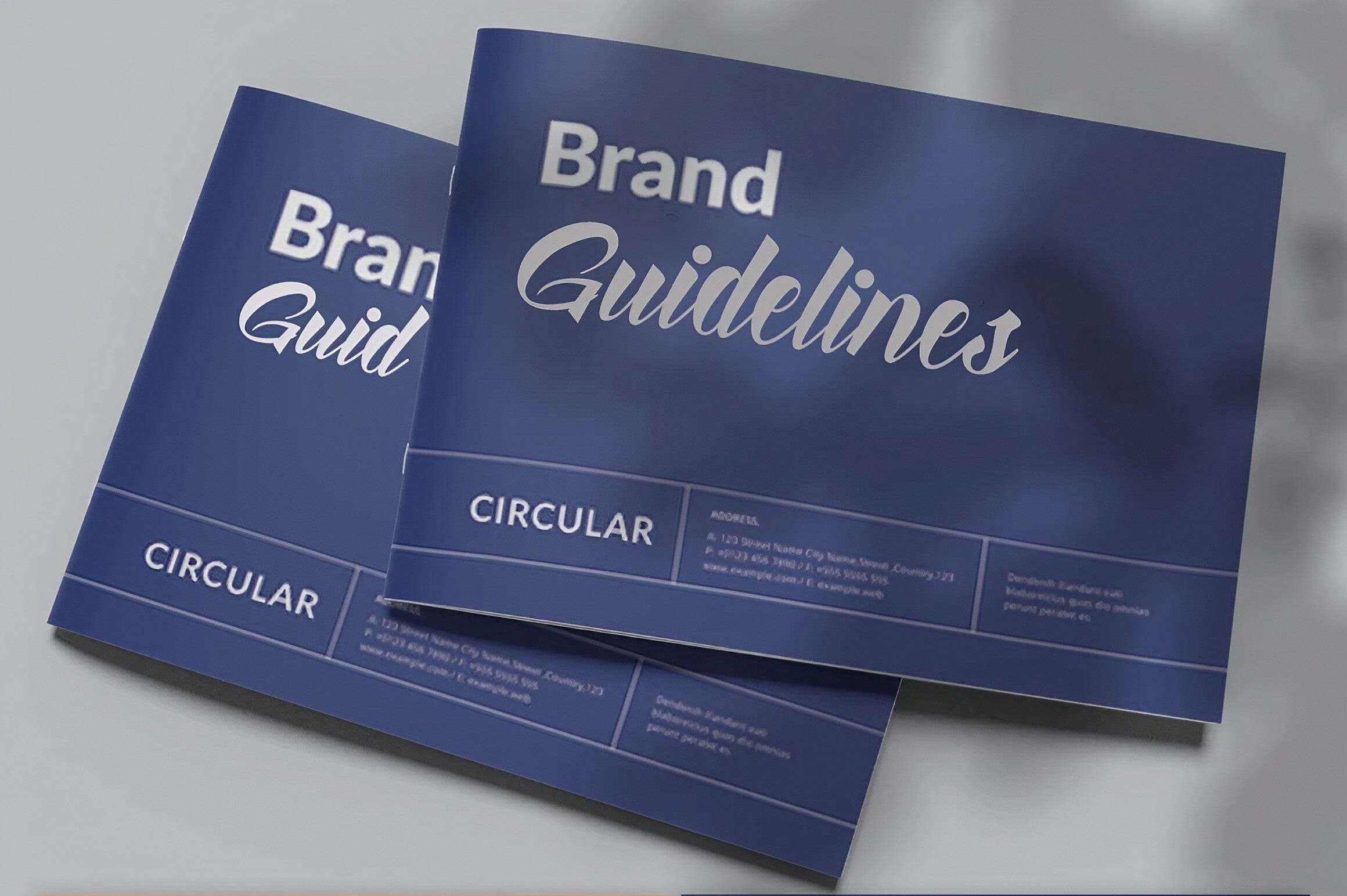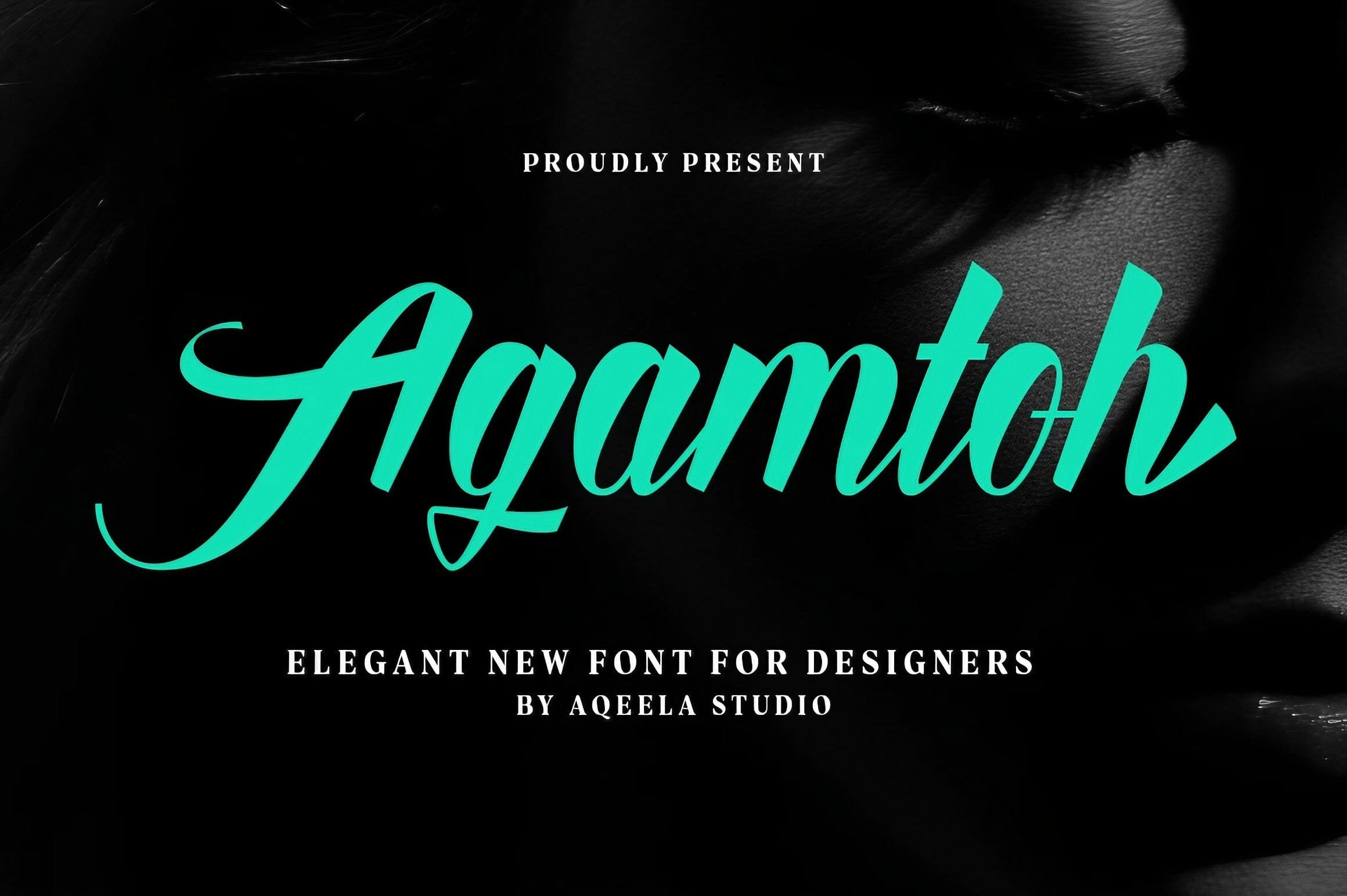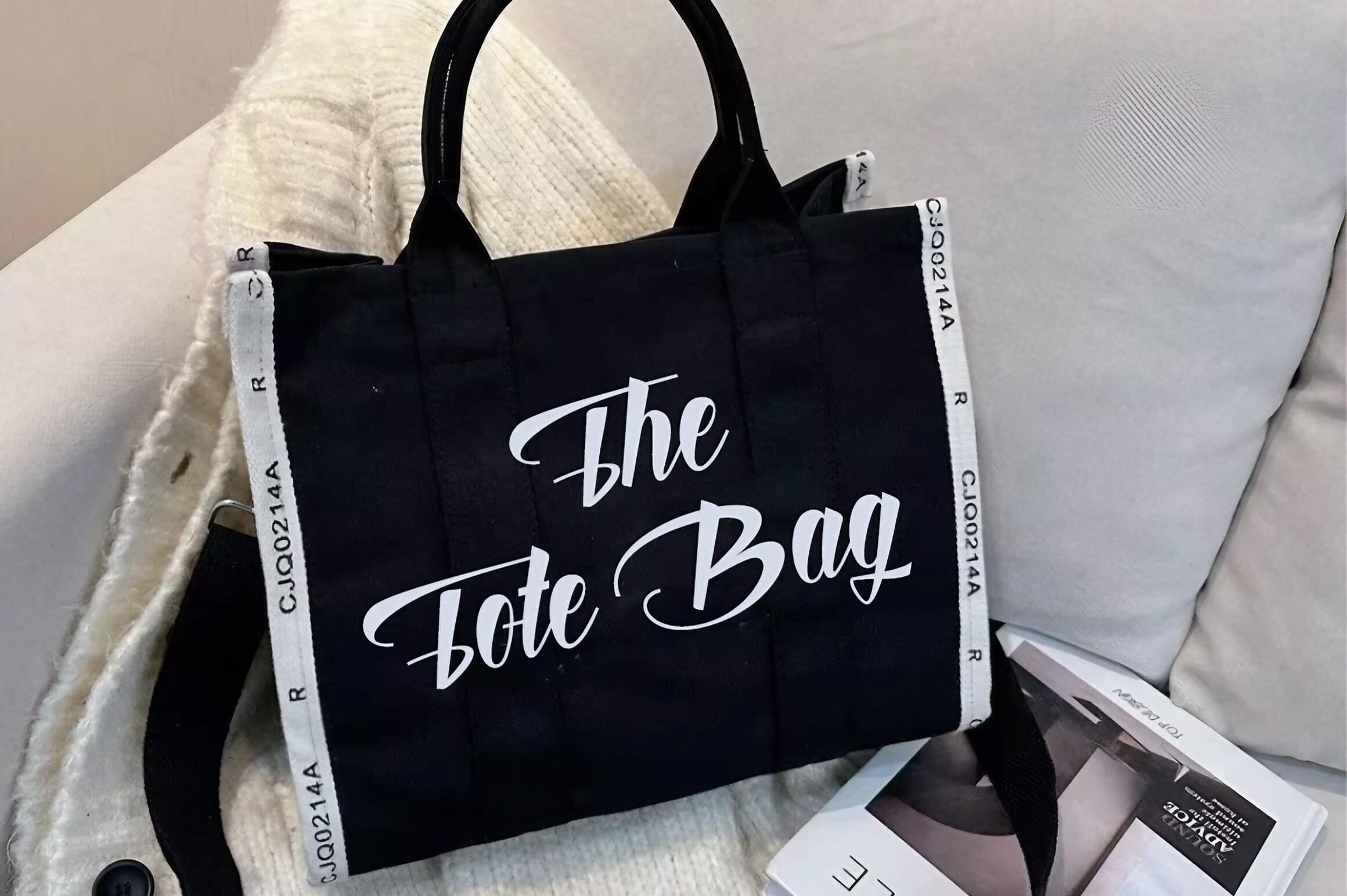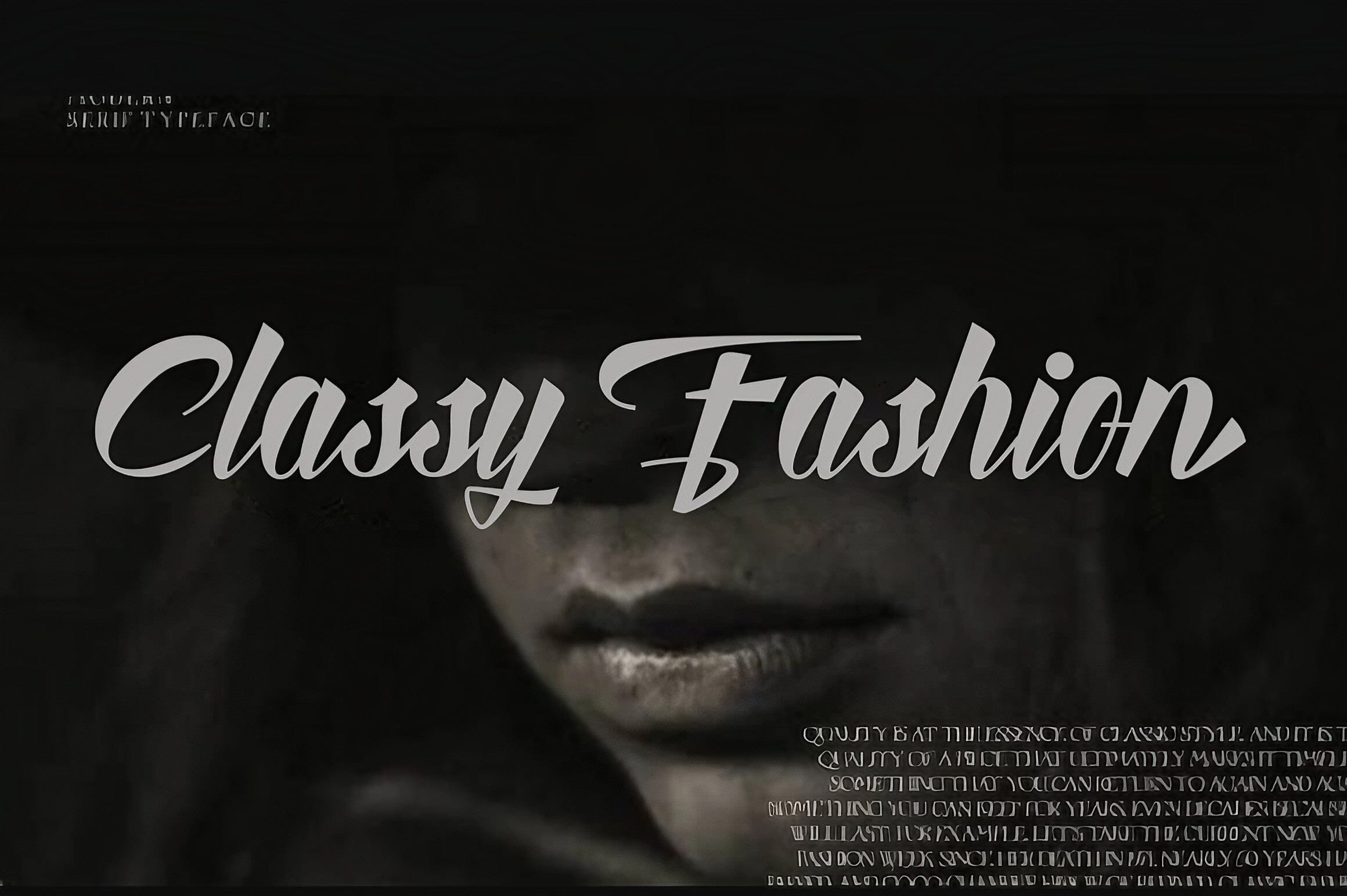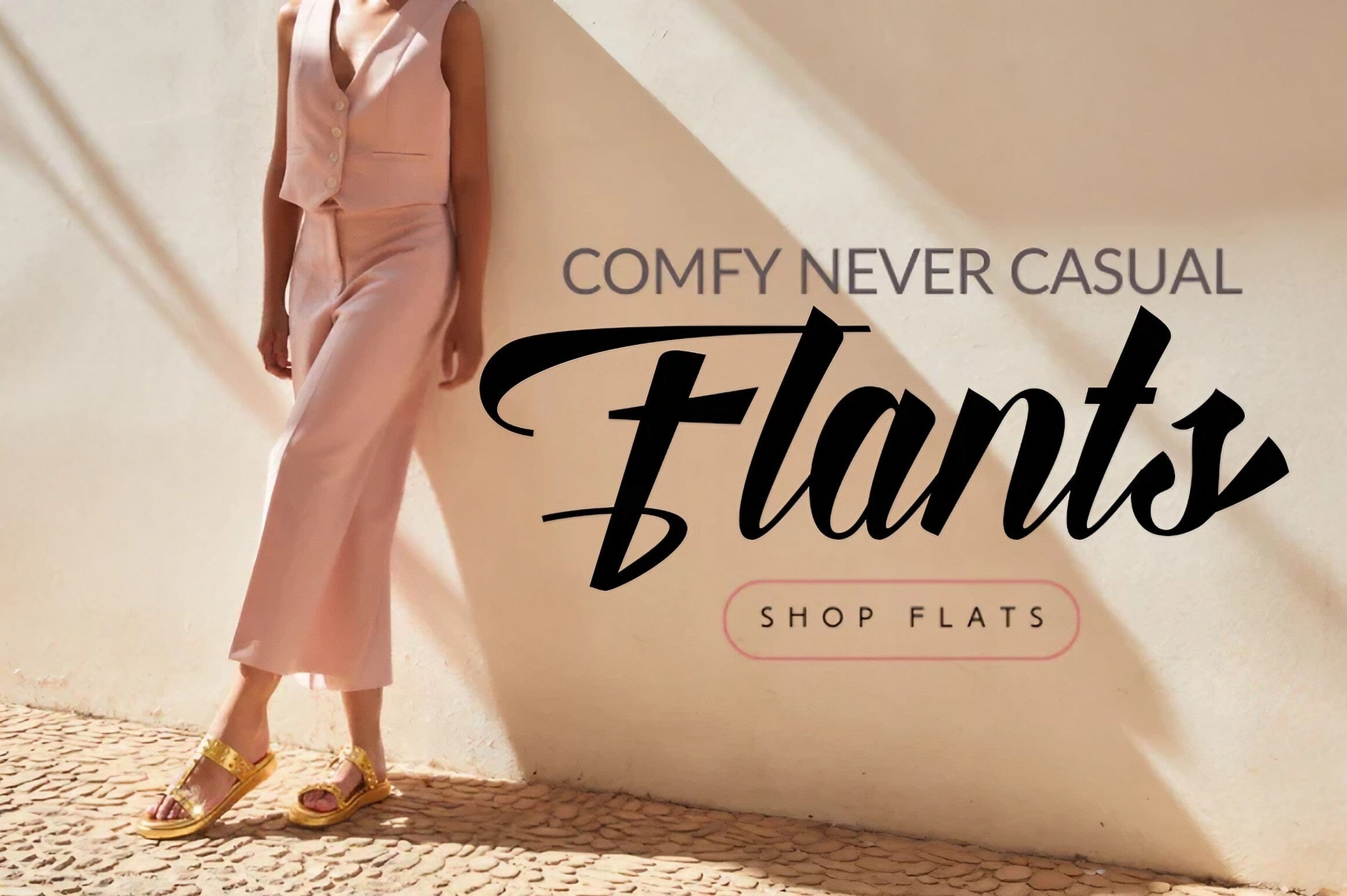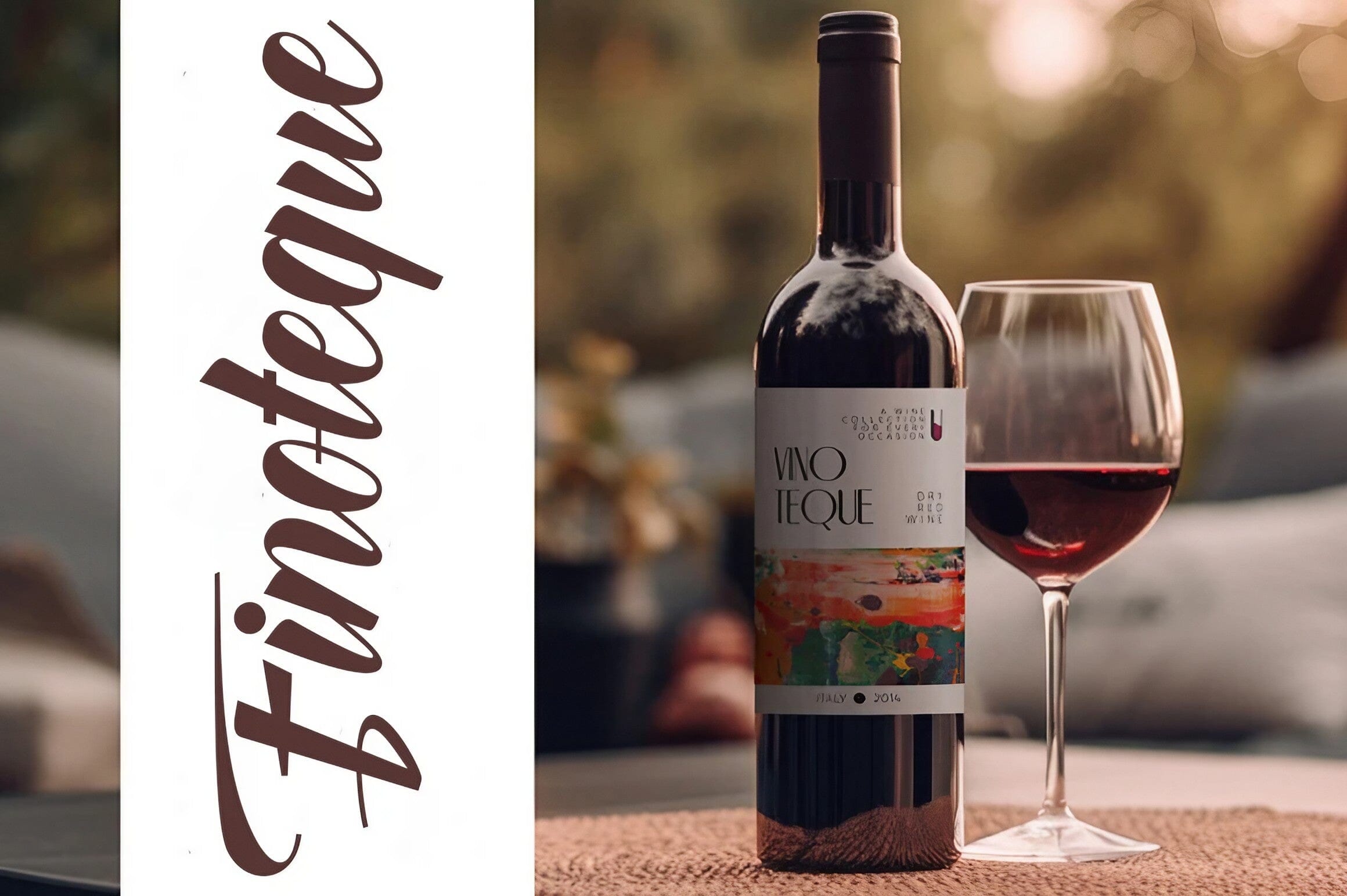
Agamtoh
About Agamtoh
Transendensikan diri Anda ke dalam perpaduan unik antara adegan klasik dan kecanggihan dengan Agamtoh kontemporer. Ini adalah font khas yang memancarkan pesona abadi dan kemewahan dalam setiap lekukan yang dibuat dengan cermat. Baik Anda mendesain logo yang canggih atau membuat tajuk utama yang menarik perhatian, biarkan Agamtoh menjadi alat yang sempurna untuk menyalakan kreativitas Anda dan membuat proyek Anda menonjol. Masukkan jenis huruf yang anggun ini ke dalam karya Anda dan saksikan perpaduan antara tradisi dan modernitas, hanya dengan Agamtoh.